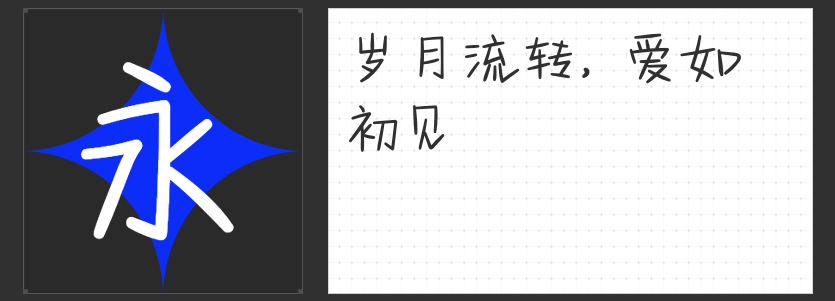
四款文艺手写字体推荐:让设计流淌手作温度与诗意美学
在数字化浪潮席卷的今天,手写字体的独特质感愈发成为设计中的“情感锚点”。它们不仅承载着书写者的温度,更能通过笔触的起落传递品牌的人文气质。以下四款风格各异的文艺手写字体,将为你的设计注入鲜活的生命力。
一、励字造仲夏简 常规
这款字体以“仲夏”为灵感,将传统书法的筋骨与现代审美的清新完美融合。笔画如竹节般坚挺爽利,边缘的斑驳处理模拟了宣纸渗透的肌理,钩笔处随性洒脱的飞白,恰似夏风拂过竹林的灵动。在茶饮包装设计中,其端正的字形能稳住视觉重心,而手写质感又中和了商业感;短视频字幕运用时,坚挺的笔画在动态中依然保持清晰可读,成为传递品牌态度的点睛之笔。
二、字青春逐梦简 准粗
字形端正中暗藏书写时的呼吸韵律,准粗的笔触既保留了铅笔书写的颗粒感,又通过适度加粗强化了视觉存在感。横画末端微微上扬的弧度,如同青春的笑靥,特别适合教育品牌或文创产品的标题设计。在内文排版中,与宋体混用能创造层次丰富的阅读体验,仿佛手写笔记与印刷文字在纸上对话。
三、贴仔初恋体
这款字体如同少女日记本上的字迹,圆润的笔画中藏着欲说还休的娇憨。倾斜的字身打破常规平衡,点画化作爱心形状,横折处自然的弧度仿佛书写时羞涩的停顿。在甜品店海报中,它能瞬间唤醒消费者的味觉记忆;儿童绘本内页使用,则让文字本身成为故事的一部分。
四、MyFont求假期简 细体
纤细柔软的笔画让人联想到作业本上的铅笔字,无过多装饰的设计却因真实而动人。圆润的转折处保留了孩童写字时的笨拙可爱,特别适合校园主题或手账风格的设计。在旅行Vlog封面中,这款字体能唤起观众对青春旅行的共鸣;手作工作室宣传物料运用时,其质朴气质与天然材料相得益彰。
当设计需要突破冰冷的技术感,这些手写字体便是最好的情感媒介。它们用笔触的粗细、转折、飞白讲述着不同的故事,让观者在方寸之间触摸到书写者的心跳。选择适合的手写字体,就是为设计注入独一无二的灵魂。